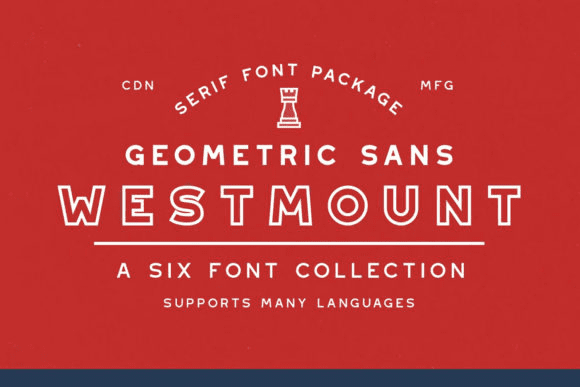
Westmount - это крутой, смелый и винтажный шрифт без засечек.
Его можно легко подобрать к невероятно большому набору проектов, поэтому добавьте его к своим творческим идеям и обратите внимание, как он их выделяет!